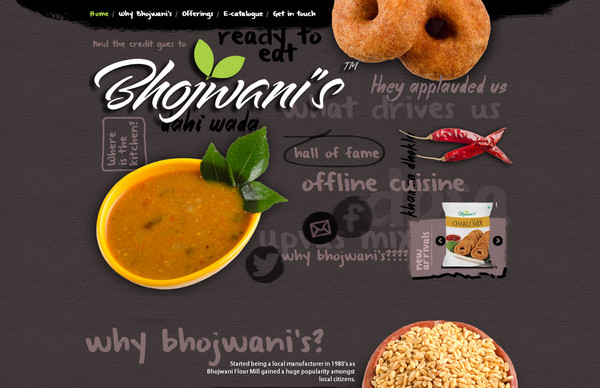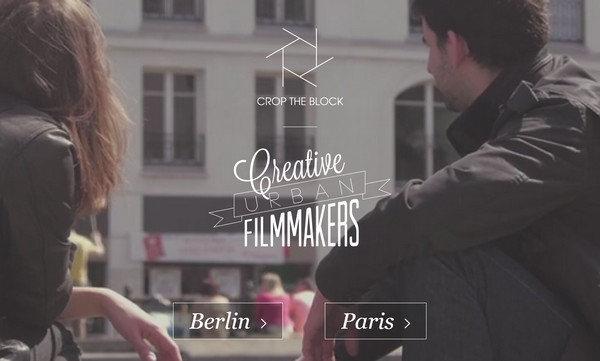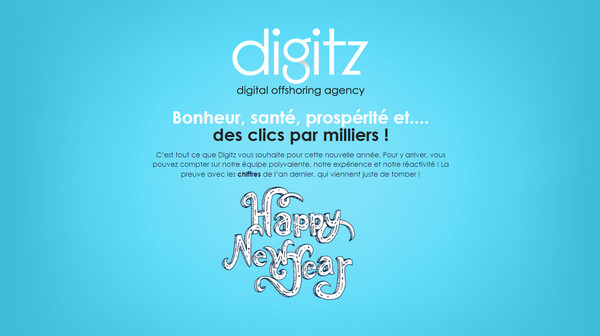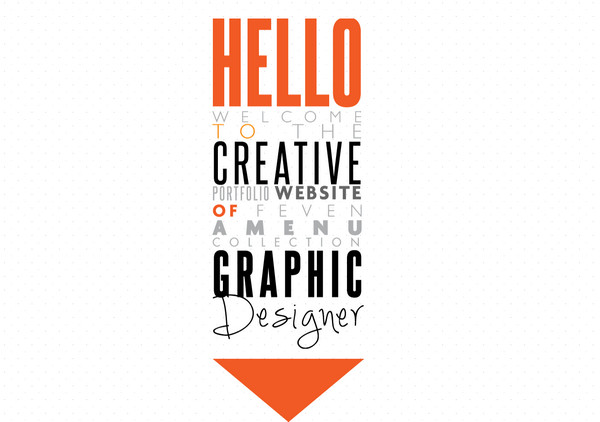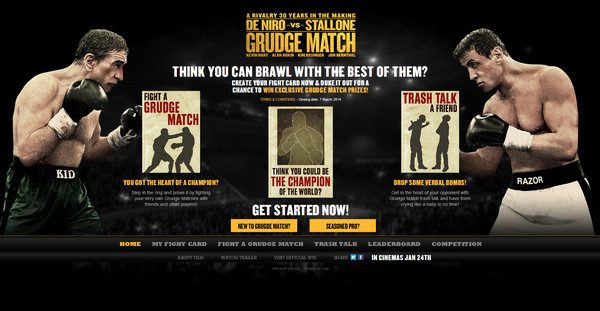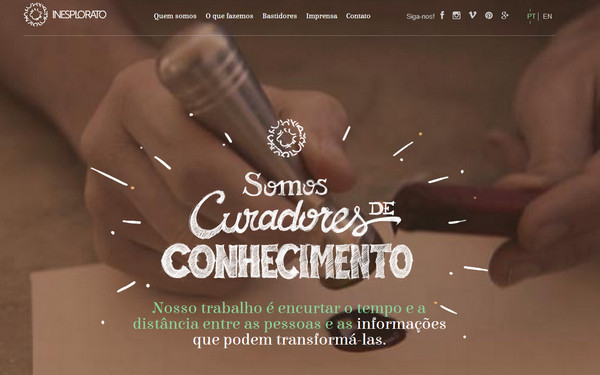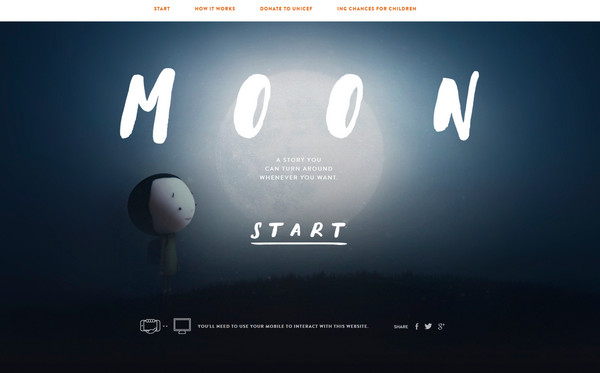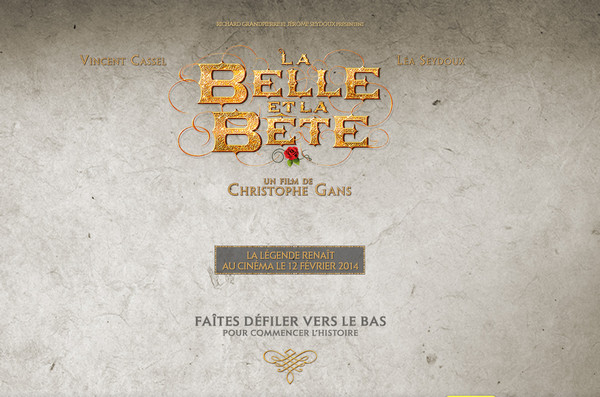
Nghệ thuật hòa trộn nhiều font chữ trên cùng một website (P.1)
Typography hoặc là giúp cho thiết kế website đẹp lên hoặc là phá vỡ nó.
Nắm vững nghệ thuật kết hợp các font chữ, đặc biệt trong thiết kế web chuyên nghiệp là điều rất quan trọng. Với hàng ngàn kiểu chữ khác nhau mà bạn có thể lựa chọn để kết hợp trên một website, bạn phải thực sự tỉnh táo và có con mắt nhìn tinh tế để chọn được những font chữ đẹp, hài hòa và tôn vinh được nhau, cũng như tôn được vẻ đẹp của website đó. Ngay cả khi bạn chỉ sử dụng một font chữ cho cả trang thì điều đó cũng không làm giảm đi khả năng sáng tạo.
Typography hoặc là giúp cho thiết kế website đẹp lên hoặc là phá vỡ nó. Hôm nay chúng tôi sẽ giới thiệu với các bạn một số website thành công và sáng tạo trong việc kết hợp nhiều font chữ khác nhau cũng lúc. Câu chuyện sẽ bắt đầu từ đơn giản với những website chỉ có 2 kiểu chữ và cuối cùng sẽ lên tới 4-5 kiểu chữ.
Space Needle có màn hình chào đó gồm vài thành phần gọn gàng được tạo bởi các font khác nhau. Chữ in nghiêng, hẹp tạo nên sự tương tác tuyệt vời với nhau và hoàn toàn hợp với bức ảnh nền mang đậm chất thành thị.
ING Direct có landing page thể hiện cảnh ban đêm đáng yêu và sử dụng font chữ tuyệt đẹp. Người thiết kế đã chọn kiểu chữ đậm, mượt mà và dễ dàng hợp với phần nội dung.
Inesplorato có tagline theo phong cách viết phấn tuyệt đẹp, không chỉ làm nổi bật trang chủ mà còn phu hợp với phần ảnh nền, một font chữ đậm chất nghệ thuật.
Digitz sử dụng trải nghiệm với 2 font chữ để khiến trang chính mang dáng vẻ của một thiết kế website thương mại, cùng lúc đó mang lại tâm trạng lễ hội.
Bhojwani Foods sử dụng rất nhiều đồ họa, ảnh chụp và chữ cái được kết hợp khéo léo với nhau. Mặc dù mới nhìn vào bạn sẽ thấy một chút hỗn loạn và qúa nhiều dữ liệu nhưng thực tế mọi thứ đều có trật tự với vai trò dẫn đầu của typography.
Feven Amenu là một online portfolio gọn gàng, rộng rãi và cân bằng tốt. Các trang con và trang chính thể hiện sự lựa chọn chính xác font chữ.
Crop the Block sử dụng khu vực hero ngay lập tức mang lại không khí thành thị. Logotype, tagline và nút call to action nổi bật với nền video và thu hút mọi ánh nhìn. Font chữ không phải được chọn ngẫu nhiên mà đều có sự hỗ trợ tốt cho việc trình bày thông điệp.
Pathfinders là một hãng quảng cáo và marketing và họ sở hữu online portfolio này. Mỗi khu vực đều sở hữu font chữ hài hòa, giúp làm nổi bật nội dung cũng như phần trang trí.
Grudge Match đã trình bày được nhiều nội dung một cách tốt đẹp. Mặc dù các dữ liệu được nhóm vào với nhau nhưng bạn có thể dễ dàng đọc được nhờ font chữ, độ rộng và màu sắc.
La Belle et la Bete với font chữ màu vàng đẹp mắt và kết hợp với texture thông minh ở background. Ngoài ra còn một font chữ thứ hai tương đồng với tên của bộ phim.